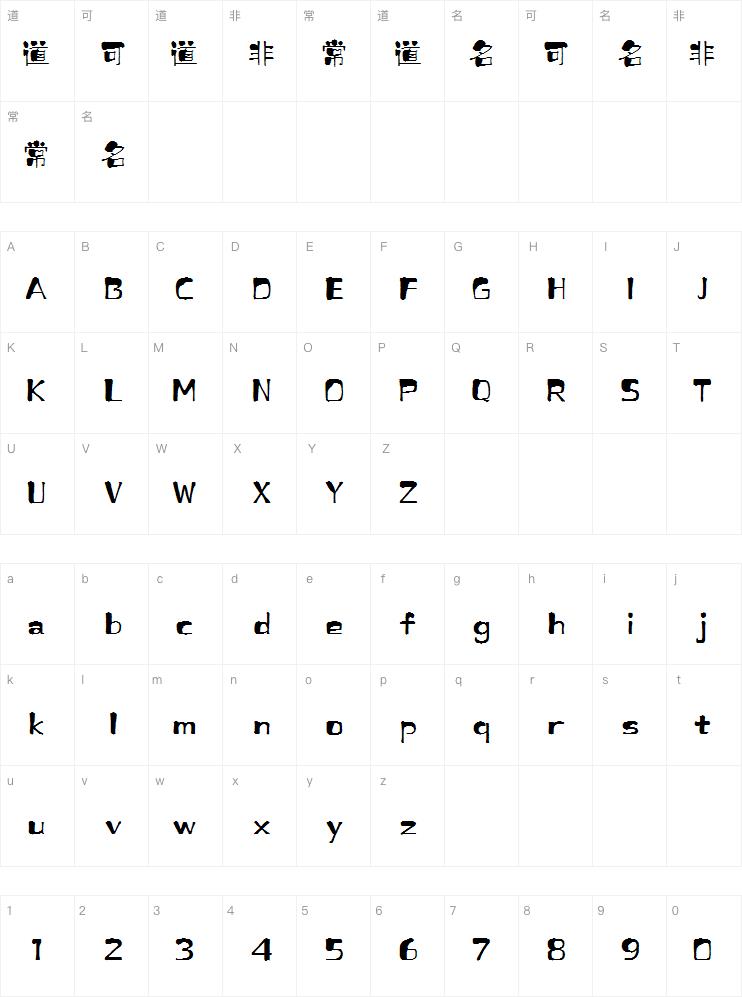
上首哆啦手写体,简体中文约6763字。这套字体以古朴韵味为底色,融入现代萌趣设计理念重塑字形。将起笔 “蚕头” 简化为圆润小顿角,收笔 “燕尾” 弱化尖锐形态,转为柔和的短弧收尾,让笔画既存隶书韵味,又添憨态。竖画、撇捺等笔画适度加粗、截断,如竖画末端以利落平切收笔,制造 “积木块” 般的稚拙感,使字体线条在古朴中透出灵动。